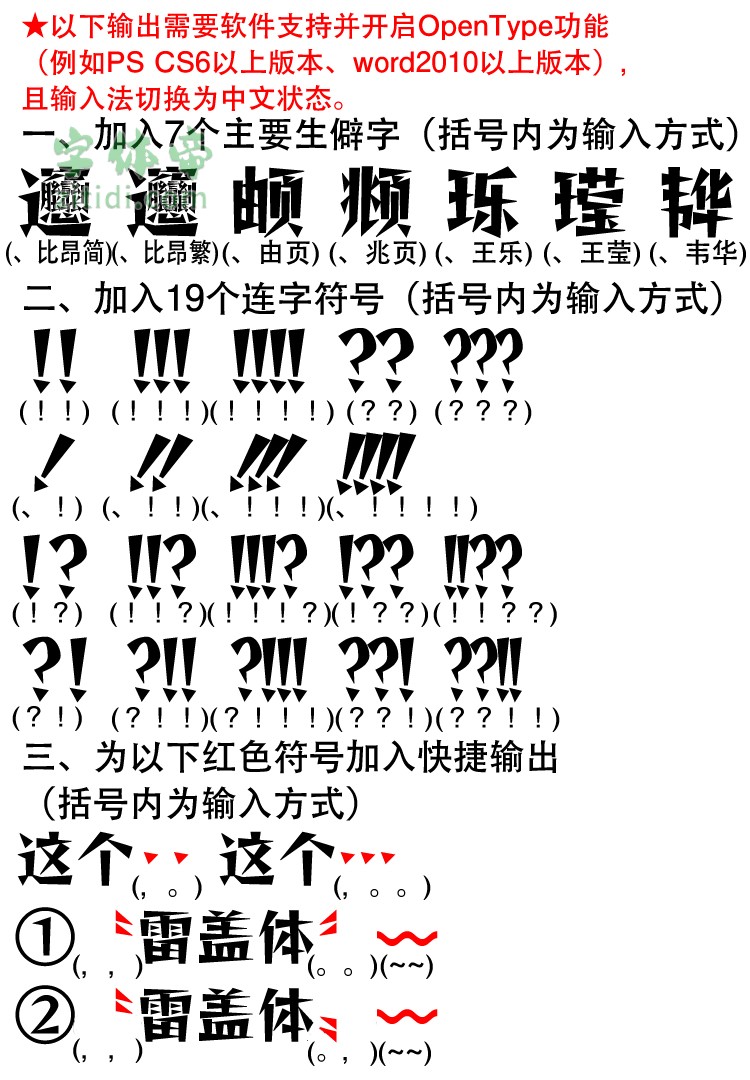
雷盖体”是根据日本著名字体设计公司Fontworks免费开源的一款字体“日文名:レゲエ,英文名:Reggae”修改,取音译“雷盖”命名而成。字体主要以补全缺失的简体汉字和部分繁体字为主,同时视情况将部分字改为国标字形标准,部分字保留原字体风格不做修改。
此版本为雷盖体2.0完整版,可输出GB2312-80国家标准字符集6763个汉字和部分繁体字。相比此前的1.0试用版进行了优化和调整,并更正错误字形,另外还加入部分OpenType个性化输出功能,因此请各位下载新完整版使用。
“雷盖体”是一款书写很新颖的字体,字体大方,适合各种设计作品使用!欢迎下载!